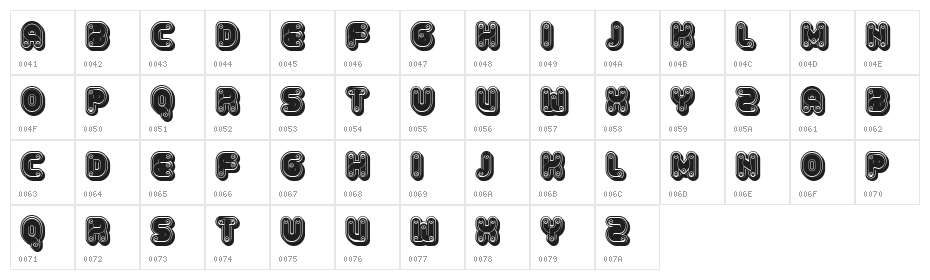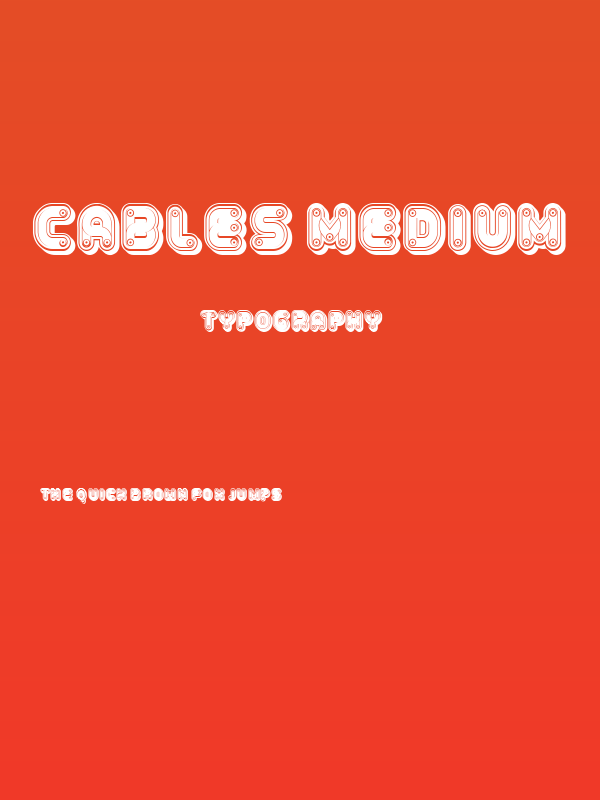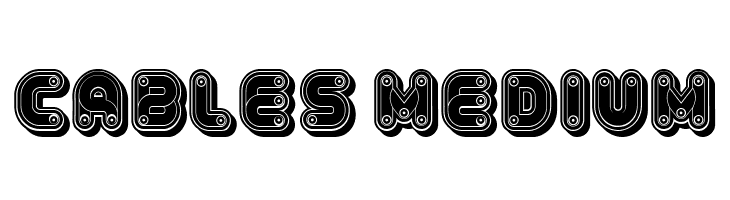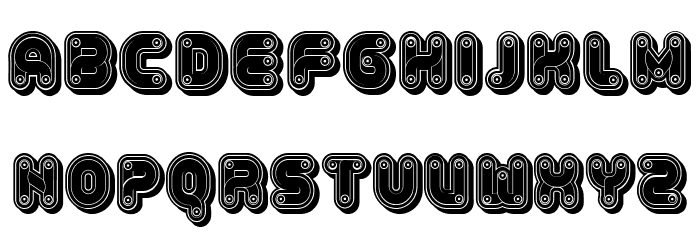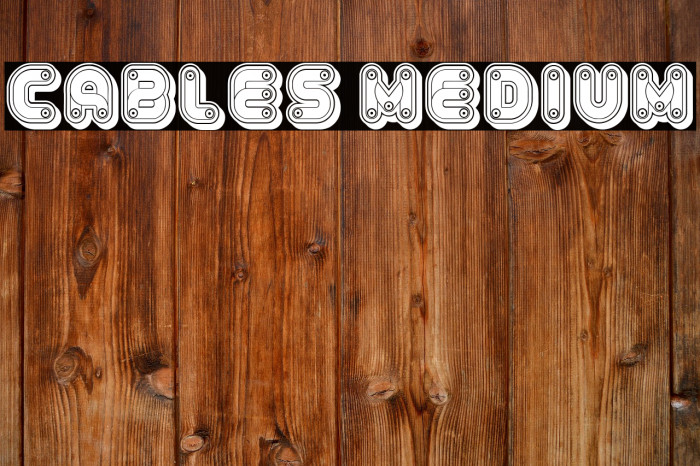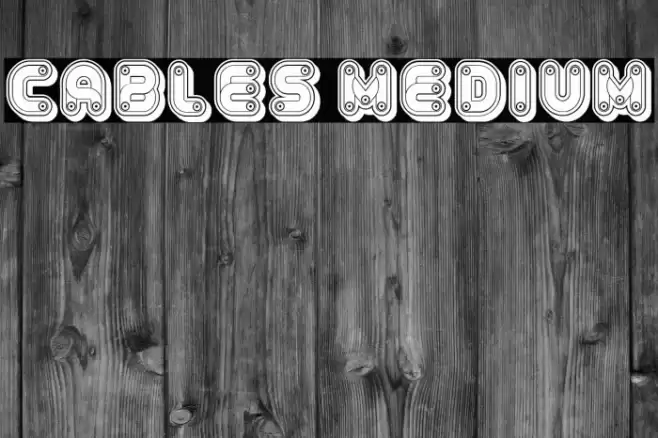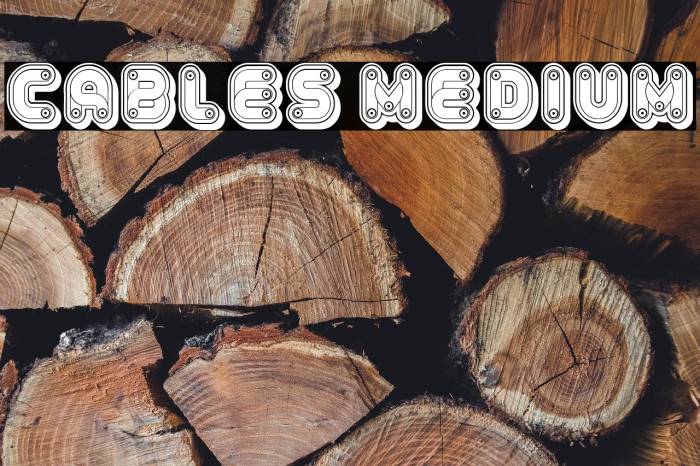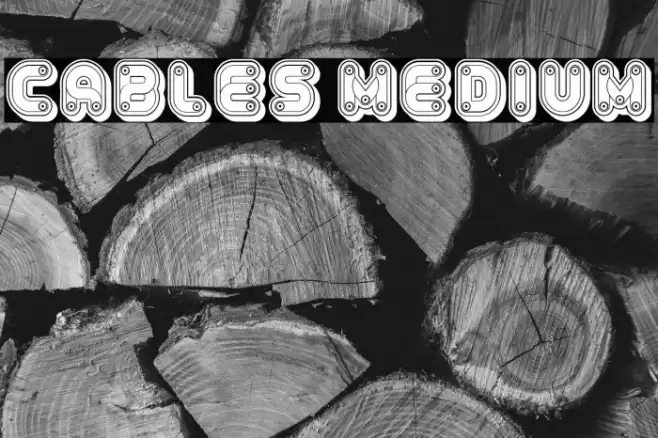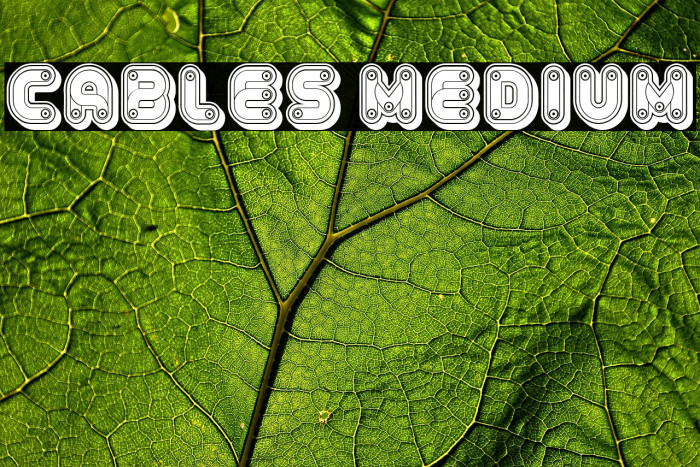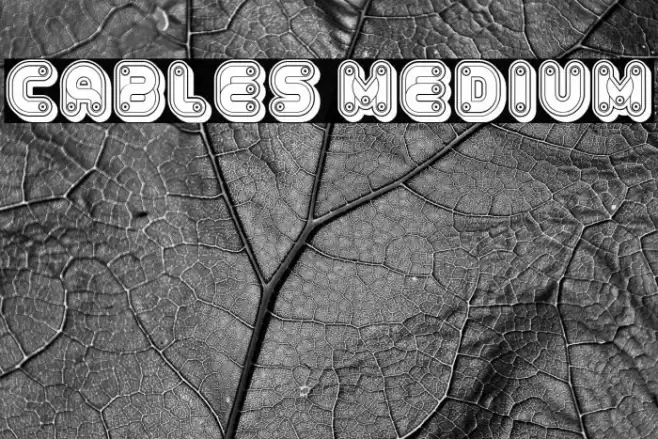
Cables Medium Font
| 全体的なスタイル | Modern, Tech-inspired |
| おすすめプロジェクト | Ideal for technology-themed posters, video game titles, branding for tech companies, and futuristic event invitations. |